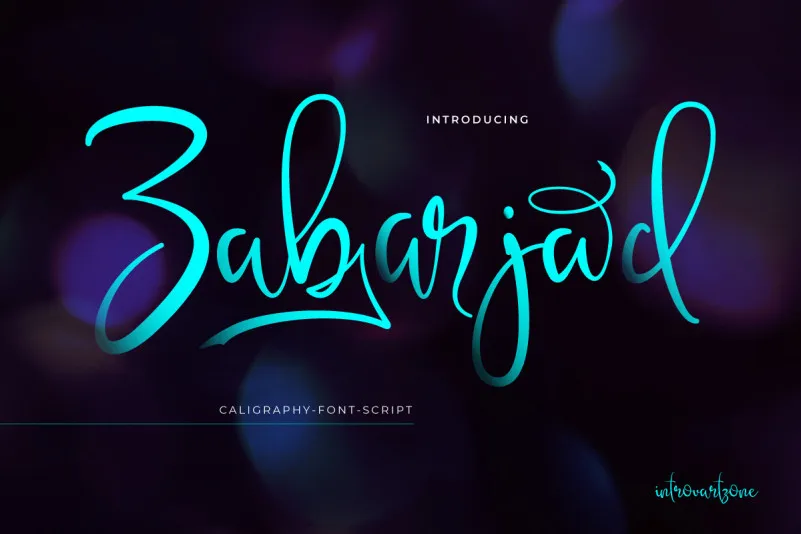
Zabarjad Handwritten Font – Download Grátis
A IntrovArtZone nos apresenta a Zabarjad Handwritten Font Script, uma elegante escolha para aqueles que procuram personalidade no seu design. Embalada com um estilo de escrever como se fosse feito à mão, esta fonte gráfica é perfeita para diversas finalidades: desde convites de casamento até criação de logotipos e identidade visual. Seja em uma página web atraente ou uma camiseta desenhada personalizadamente, Zabarjad Handwritten Font Script traz uma sensação de sofisticação e individualidade ao seu design. Ideal tanto para aqueles que buscam um toque diferente em seus projetos quanto para designers que valorizam estética cuidadosa, essa fonte é uma ótima opção para criar designs memoráveis. Seja você um designer gráfico iniciante ou profissional, Zabarjad Handwritten Font Script certamente será um recurso indispensável na sua coleção de fontes.
Designer: IntrovArtZone